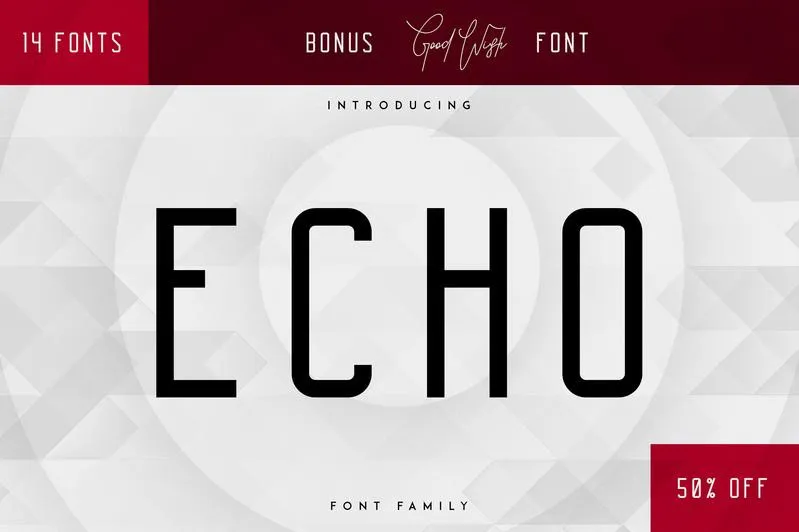
A ‘Echo 14 Font Family + Bonus’ é uma tipografia bold e poderosa do tipo sans serif com 14 diferentes tipos e suporte multilíngue. Ideal para grandes e pequenos tamanhos, esta fonte é extremamente versátil e funciona perfeitamente em vários ambientes design. Seja você um criador de materiais digitais ou impressos, a ‘Echo’ é uma escolha inteligente que enriquece seu trabalho sem comprometer o equilíbrio visual. Ideal para uso no design gráfico, web, branding, e qualquer outro projeto que exige uma tipografia robusta e confiável.